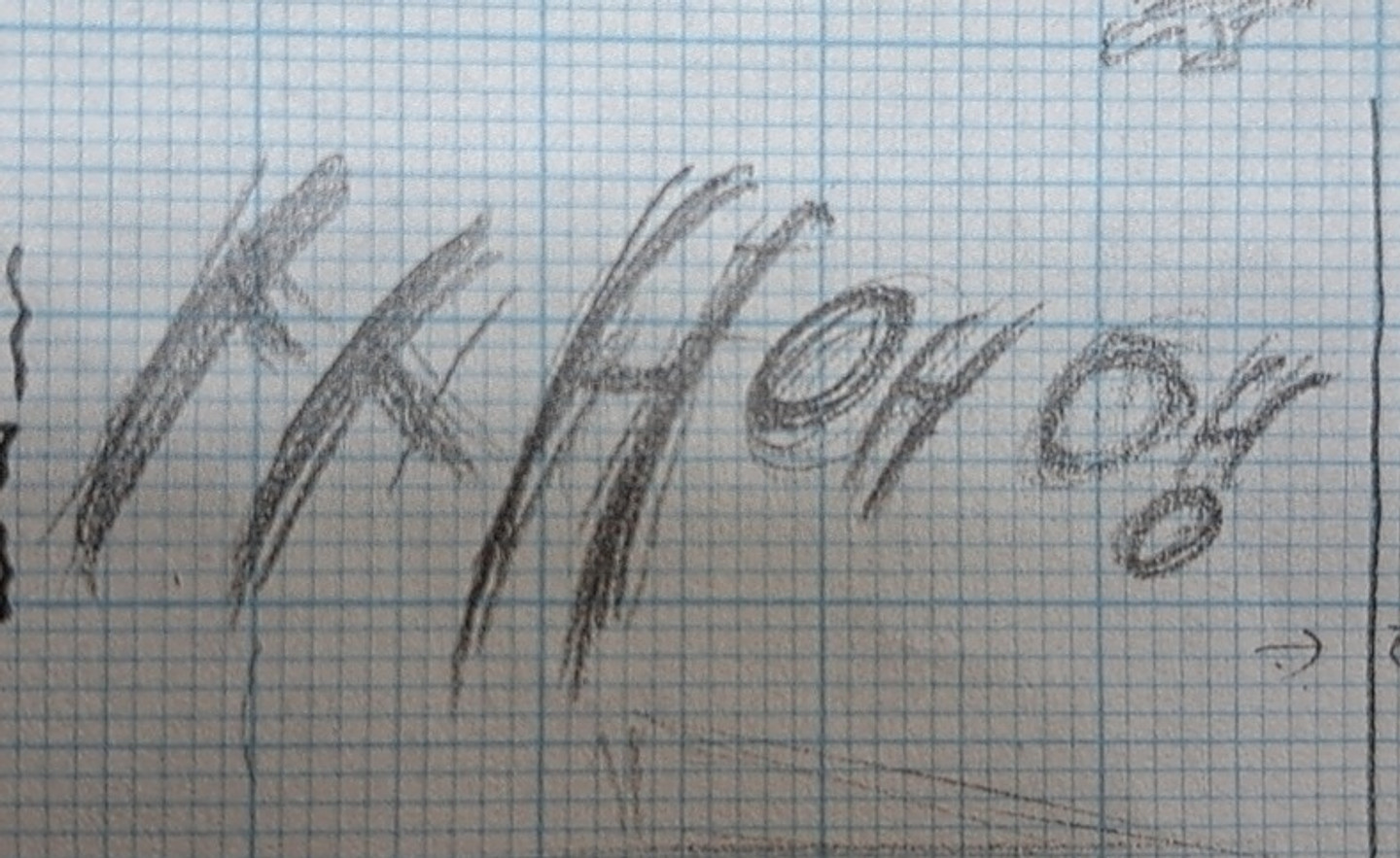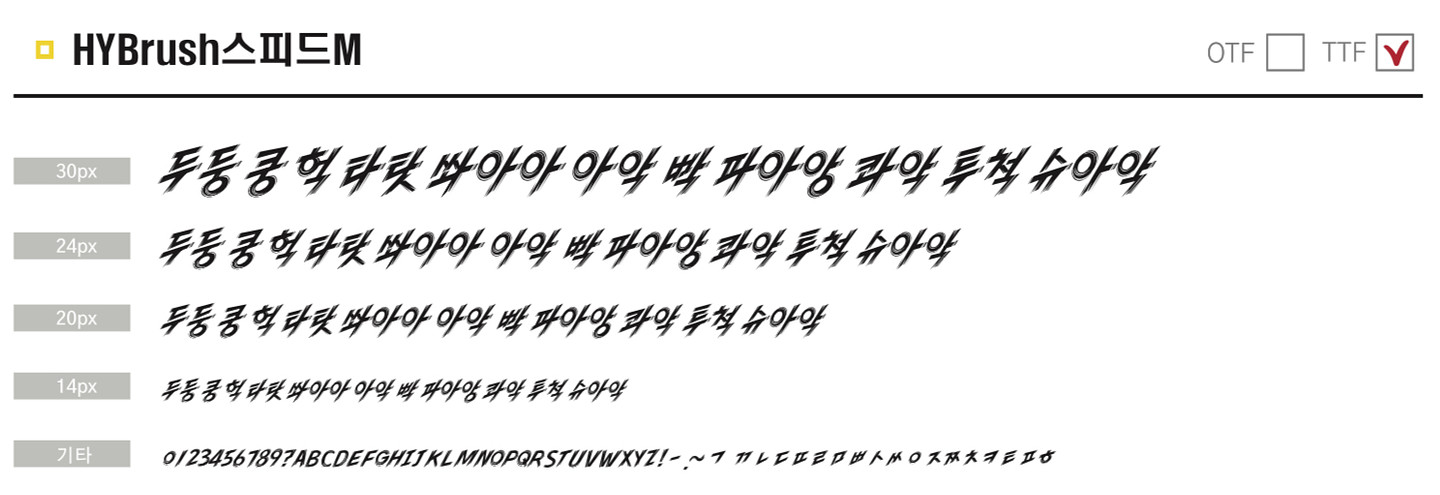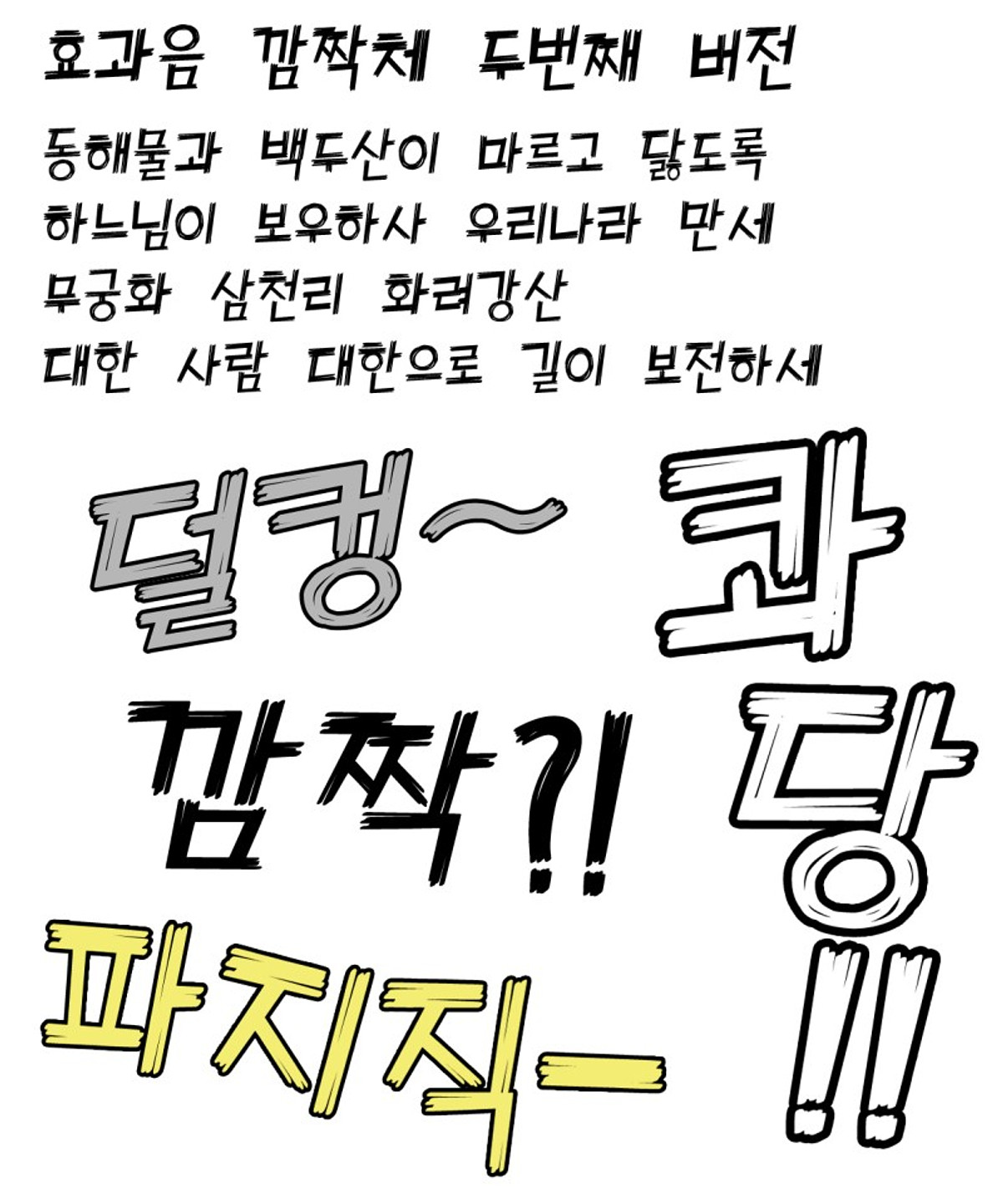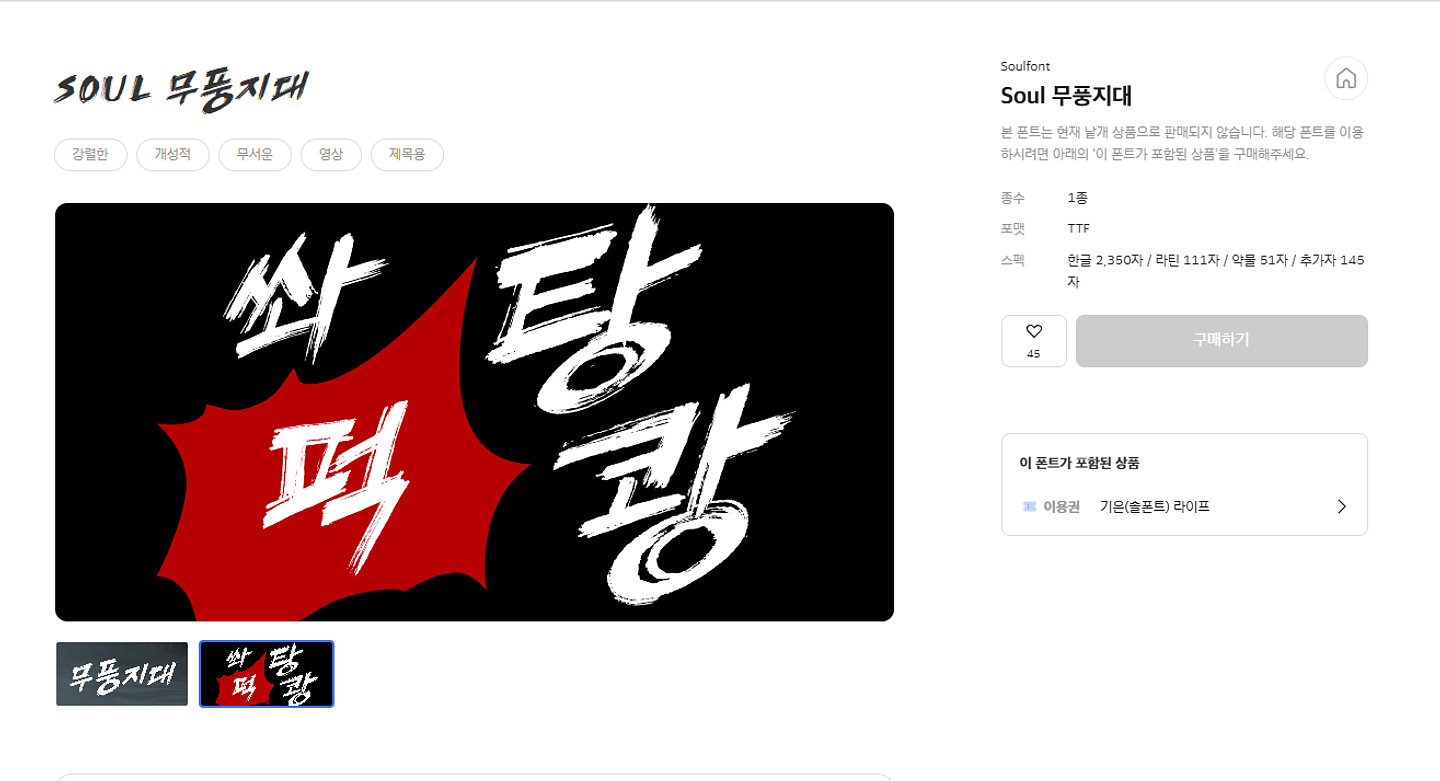
이런 식으로 생긴 폰트 이름이 뭔가요?ㅠ 웹툰이나 만화에서 효과음으로 쓰일것같은 폰트에요 거친 느낌의 여러 선을 그어 쓴 것처럼 생곘어요
HYBrush스피드
혹시 이 폰트 말씀하시는 걸까요?
깜짝체2
식자양성소의 효과음 폰트인데 이쪽이 더 비슷할 것 같습니다.
Soul 무풍지대
이친구인것 같습니다.